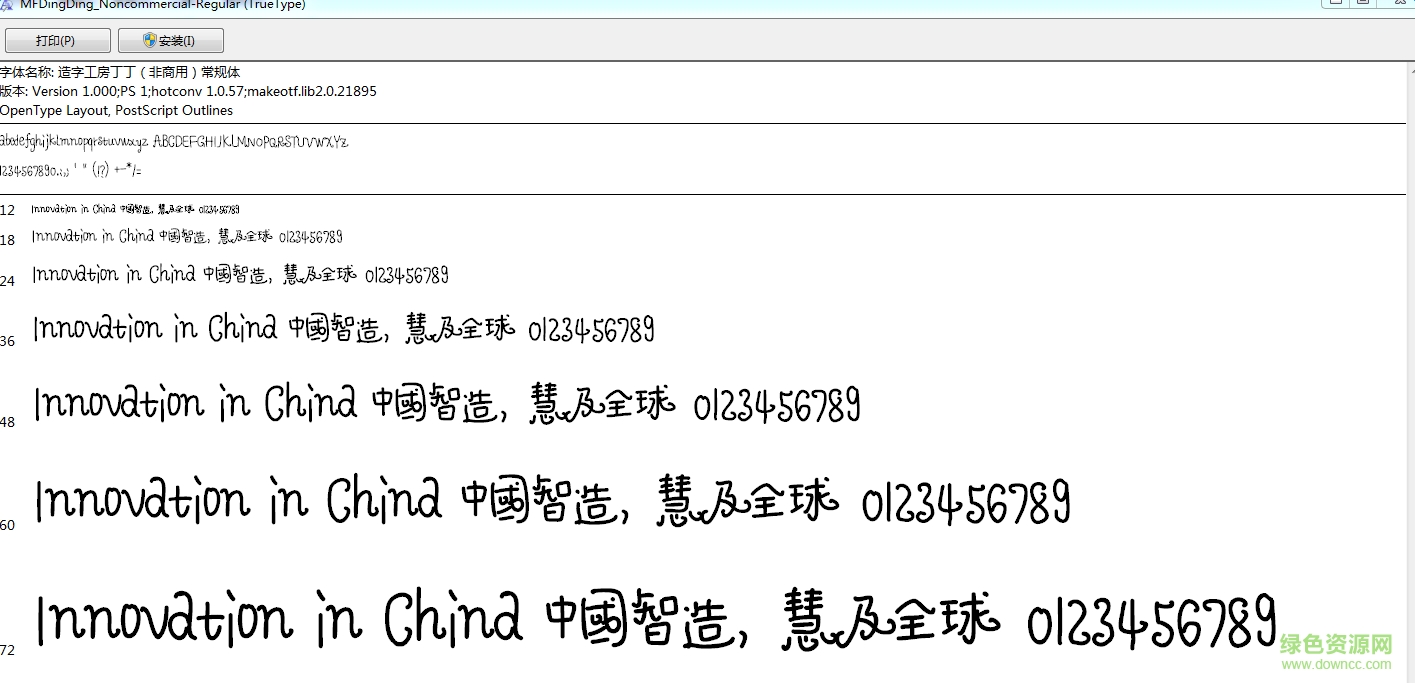
造字工房丁丁手繪體是一款造字工房類可愛風(fēng)格字體軟件,丁丁手繪體給人非常呆萌的感覺,創(chuàng)意十足,適用于各大動(dòng)漫卡通設(shè)計(jì),也深受廣大書法家的喜愛,還有更多好看字體盡情期待,歡迎到綠色資源網(wǎng)下載體驗(yàn)!
造字工房丁丁手繪體這款字體非常可愛,很適合設(shè)計(jì)行業(yè),一些卡通類的畫報(bào)等都可以用到本款字體!